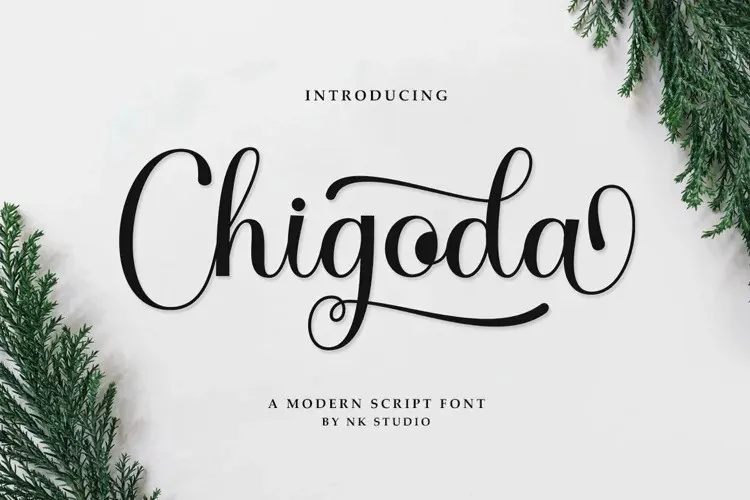
Chigoda Font – Download Grátis
A Chigoda Font é uma elegante tipografia serifada criada para adicionar um toque romântico às criações digitais. Seu design fluido e acentos refinados, inspirado no estilo do chirografista, são perfeitos para dar vida aos elementos de marca, cardes de presente de casamento ou até mesmo ao texto sobre imagens de fundo em projetos de produto embalagem. Com seus 351 glifos, a Chigoda Script oferece opções suficientemente variadas para atender à diversidade das necessidades dos criadores digitais. Perfeita para um design gráfico com toque sofisticado e elegante, ela é uma ótima escolha para aqueles que desejam dar um pouco de luxo a qualquer projeto digital.